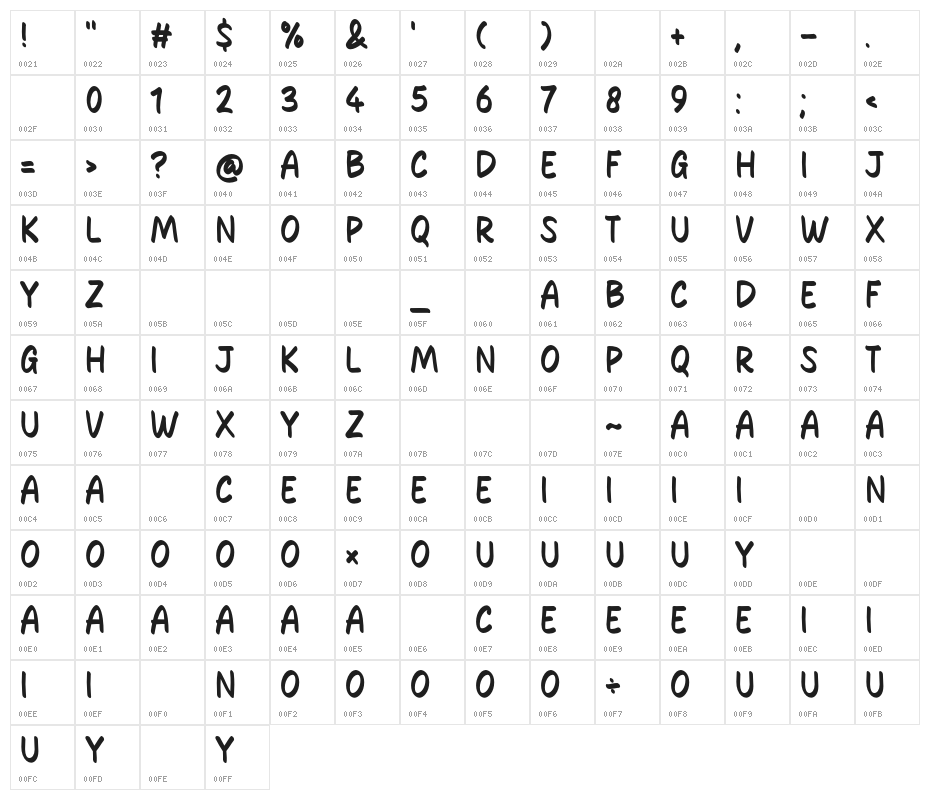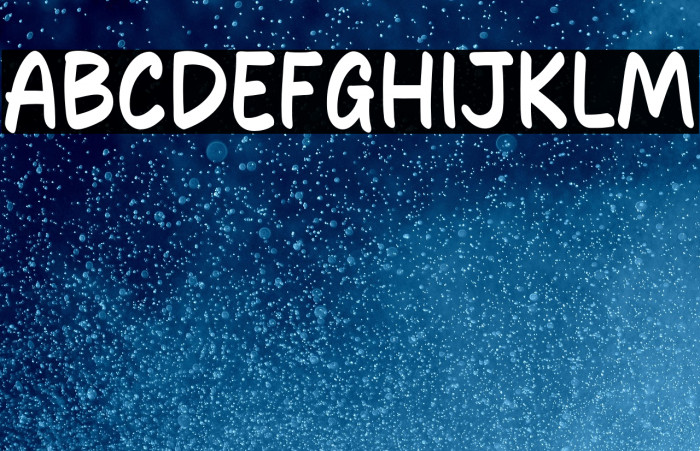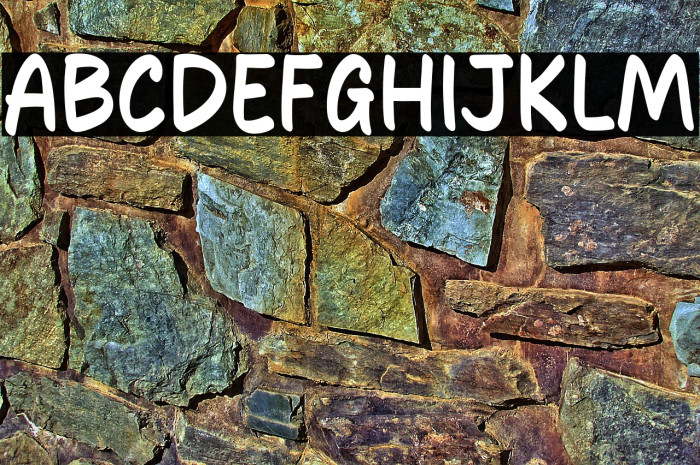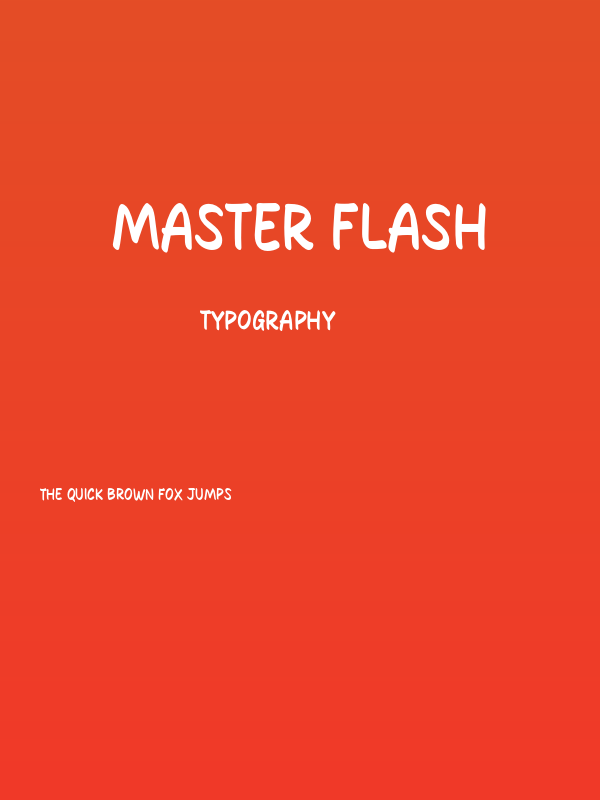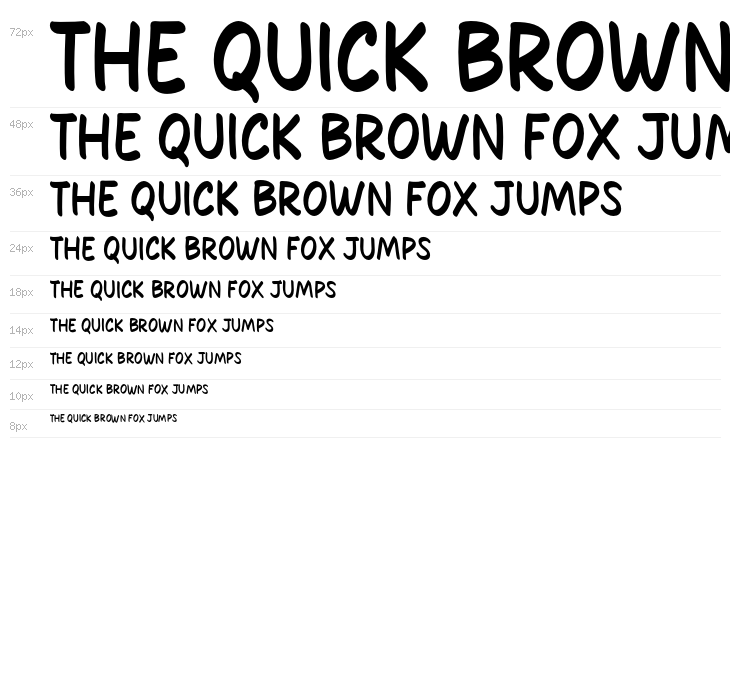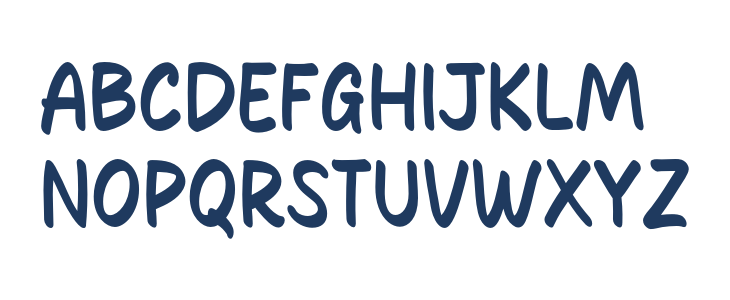
Master Flash Font
| Estilo general | Playful |
| Caso de uso | Headlines, Logos, Informal Text |
| Proyectos propuestos | Ideal for children's books, greeting cards, playful branding, and social media graphics. |